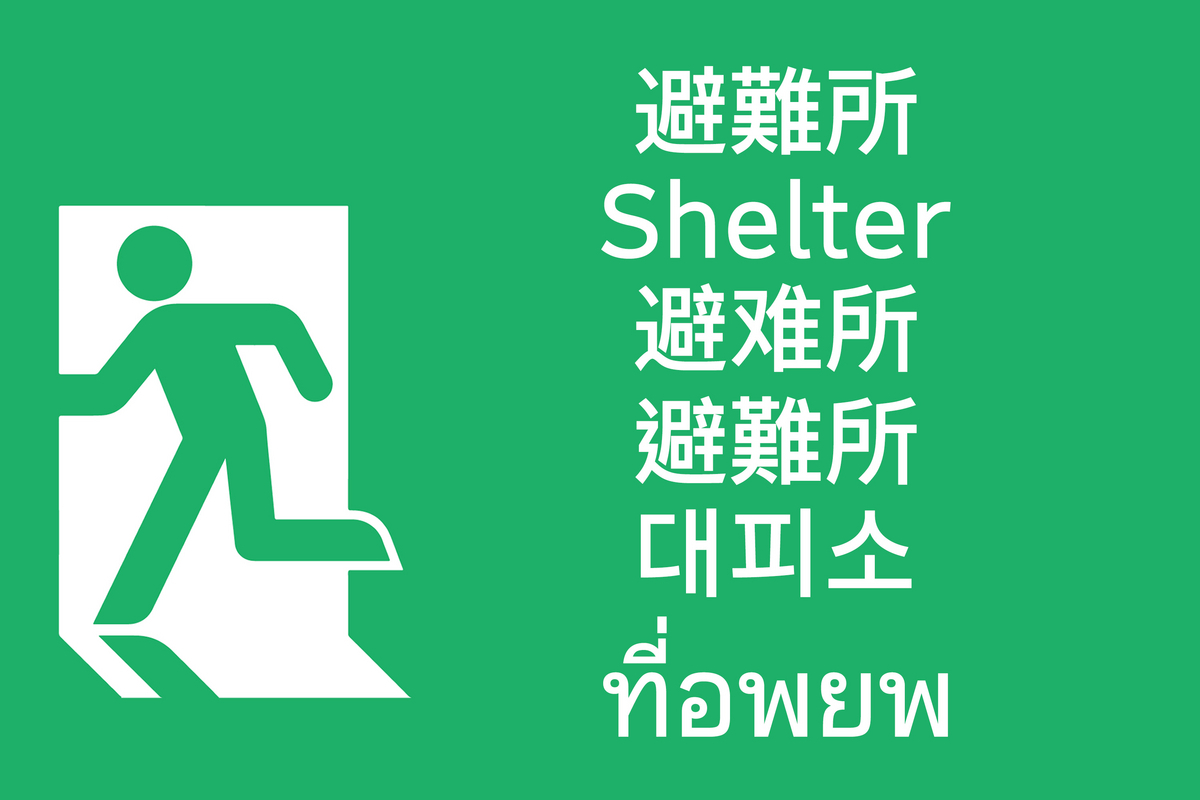
イワタの新たな多言語フォントとして、みんなの文字Globalのファミリー追加と新たな多言語フォントファミリーや中国の国家標準規格GB18030-2022に準拠したフォントを新発売
イワタは「みんなの文字Global」「イワタUDゴシック多言語対応フォント」「GB18030-2022対応フォント」を2023年10月31日に新たに発売したことを発表した。
前代未聞の円安でバイアスもかかりインバウンド需要により訪日外国人が増加している昨今。
街や公共施設には日本語と共に多言語が表示されている案内表示が多くあるが、その中には文字のデザインや太さがばらつきがあるものを多くある。
今回新発売したイワタの多言語フォントを使用することで、案内表示などにも統一感のあるデザインにすることができる。
みんなの文字Global
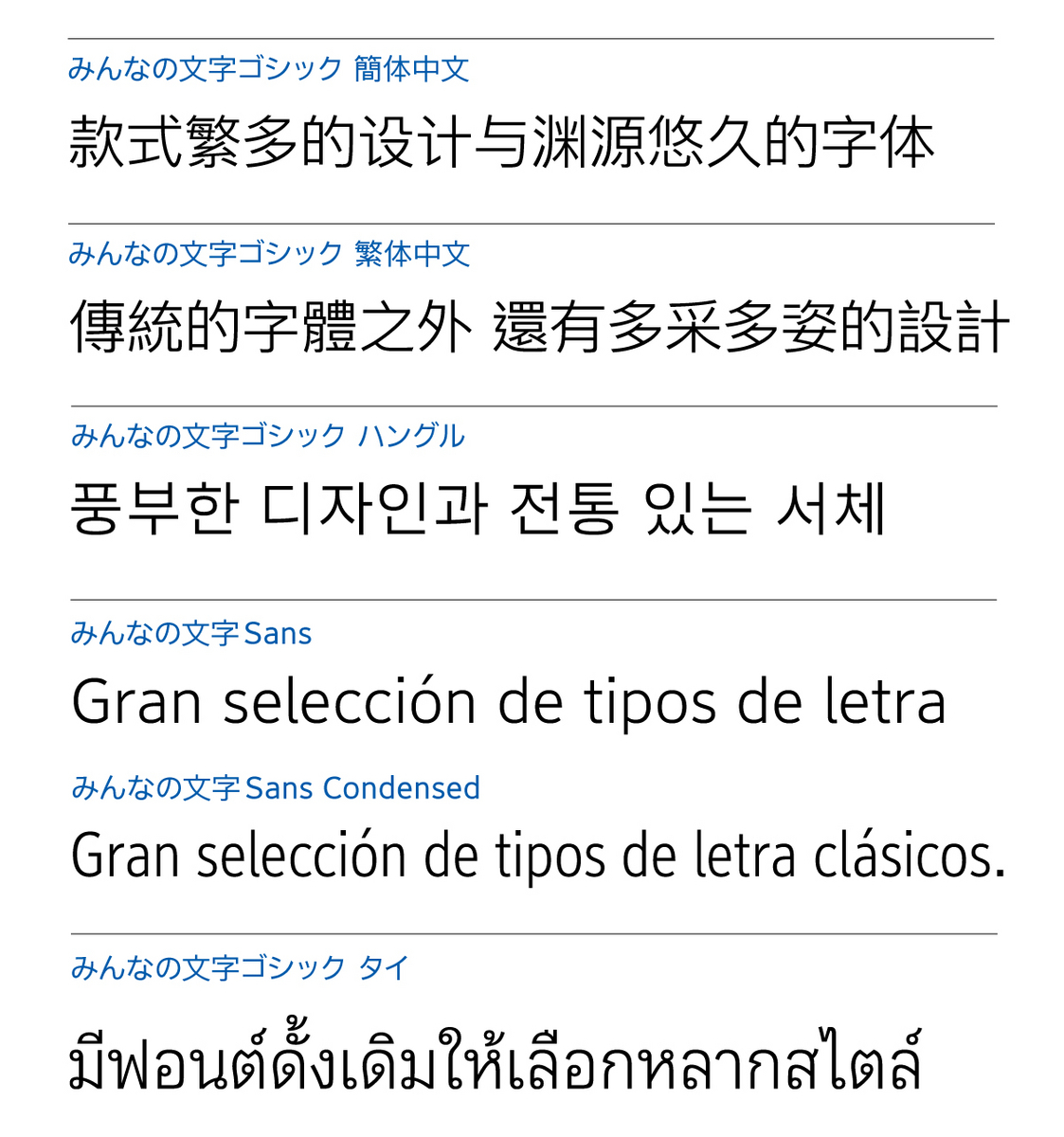
「みんなの文字Global」は「文字が小さく密集していても読みやすい」をコンセプトに開発した日本で唯一の第三者認証を取得した日本語フォント「みんなの文字」をベースにした多言語フォント。
ファミリーにタイ語(L/R/R2/M)を加え、訪日外国人が使用する言語の90%(注1)以上のサポートを可能にした。
また中国語(簡体字、繁体字)、韓国語(ハングル)では不足していた文字の太さ(L/M)を追加して各言語での統一したデザインを実現できる。
イワタUDゴシック多言語対応フォント
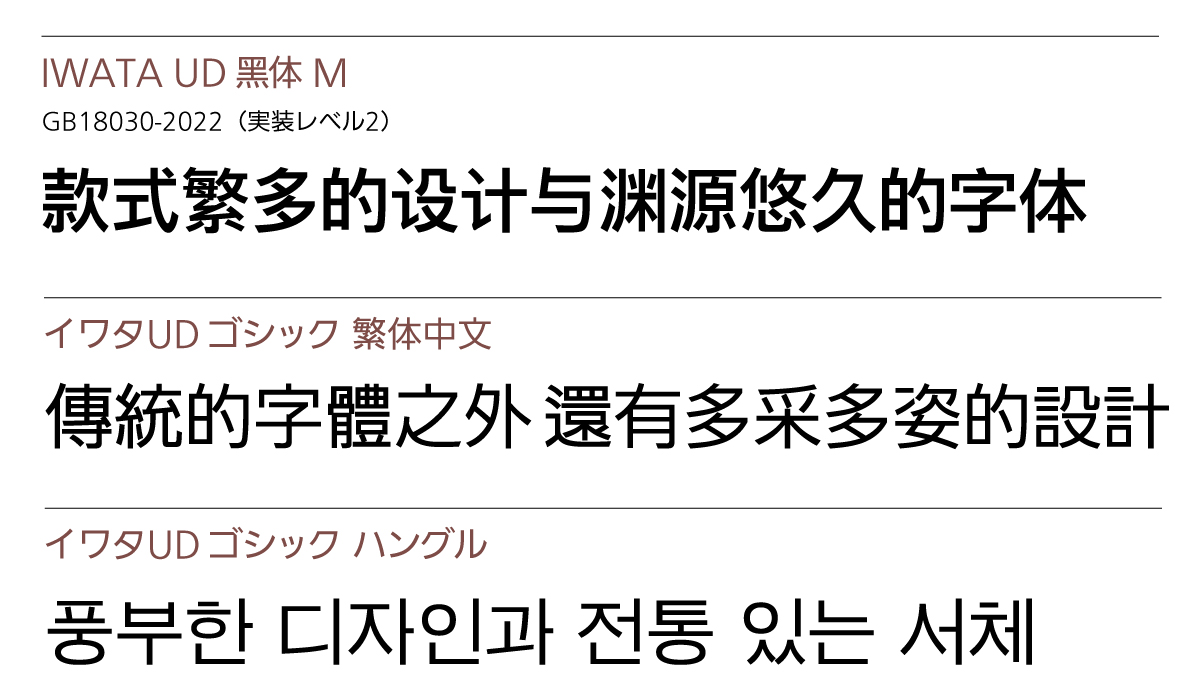
「イワタUDゴシック多言語対応フォント」は、2006年に日本で初めて「高齢者や弱視の方にも見やすいフォント」として、パナソニックとイワタで共同開発した日本語フォント「イワタUDゴシック」をベースにした中国語(簡体字、繁体字)、韓国語(ハングル)を開発した。
単語や短い文章で判読しやすい視認性に優れた文字は、サインやメニューなどで効果を発揮する。
GB18030-2022対応フォント
中国に輸出する製品や中国で販売する製品に中国語フォントを搭載する場合、中国の国家標準規格であるGBの最新規格「GB18030-2022」に準拠したフォントを使用する必要がある。
規格に対応した中国語簡体字である「IWATA UD黑体 M」「IWATA 宋体 R」も発売した。
日本国内だけでなく中国国内向け製品にも使用できる。